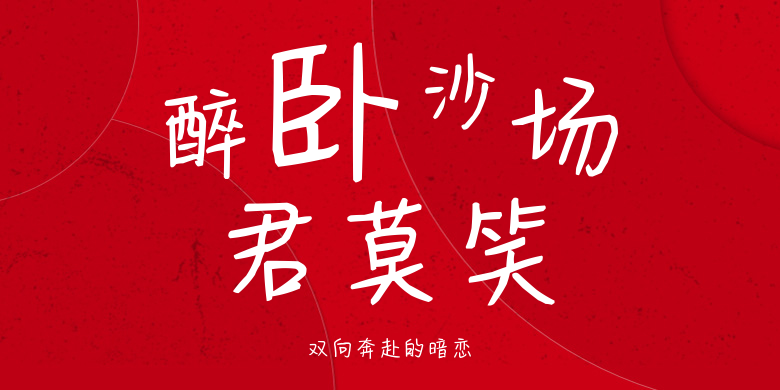
双向奔赴的暗恋
双向奔赴的暗恋,这款字体结构工整、笔画清晰,兼顾美观与易读性,适用于标题、正文、海报、包装、LOGO 等多种场景。字形优雅稳定,风格百搭耐看,适配日常排版与创意设计,让文字呈现更舒适、更具质感。双向奔赴的暗恋一笔一画,皆是细节,以均衡的比例、流畅的线条打造舒适视觉体验,字形端正大气,风格简约现代。无论是商业设计、品牌宣传还是日常排版,都能轻松驾驭,让文字更有格调与力量。双向奔赴的暗恋字体下载。